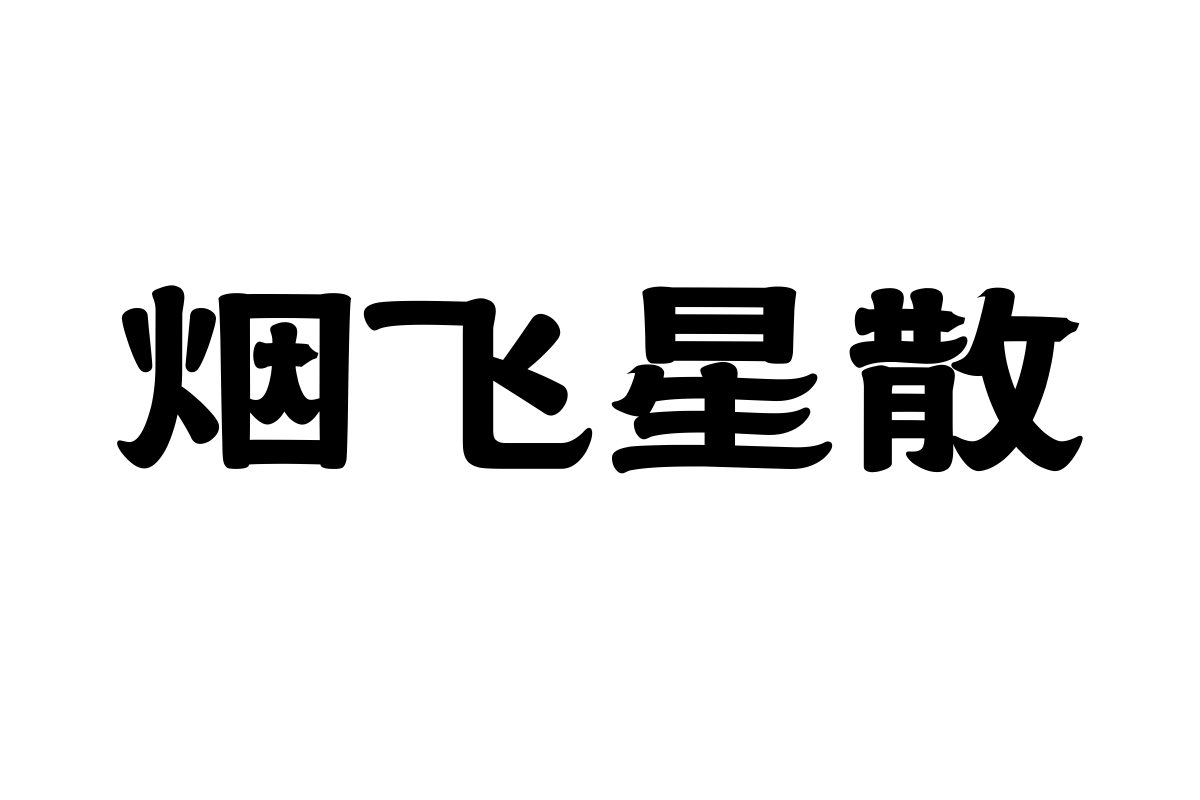
上首伯牙体是一种具有独特书法风格的字体,其特点是笔画流畅、结构紧凑,给人一种优雅而庄重的感觉。这种字体在古代被广泛应用于书法和绘画中,是中华文化的重要组成部分。
上首伯牙体的特点包括:
1. 笔画流畅:该字体的笔画线条流畅自然,没有过多的弯曲和折角,给人一种轻松愉悦的感觉。
2. 结构紧凑:该字体的结构紧凑,字与字之间留有适当的空间,使得整个字形显得更加饱满而有层次感。
3. 优雅庄重:上首伯牙体给人一种优雅而庄重的感觉,适合用于正式场合和传统文化氛围的展示。
4. 易于辨识:该字体的笔画和结构具有一定的规律性,使得读者容易辨认和记忆。
总的来说,上首伯牙体是一种具有独特魅力的字体,适合用于书法、绘画和各类文化作品的创作和展示。